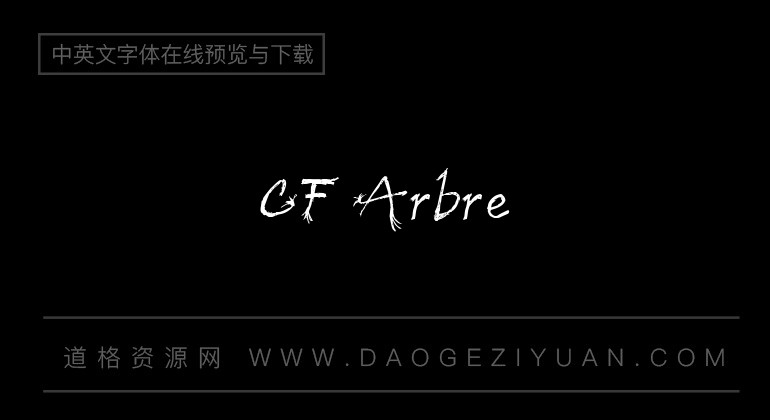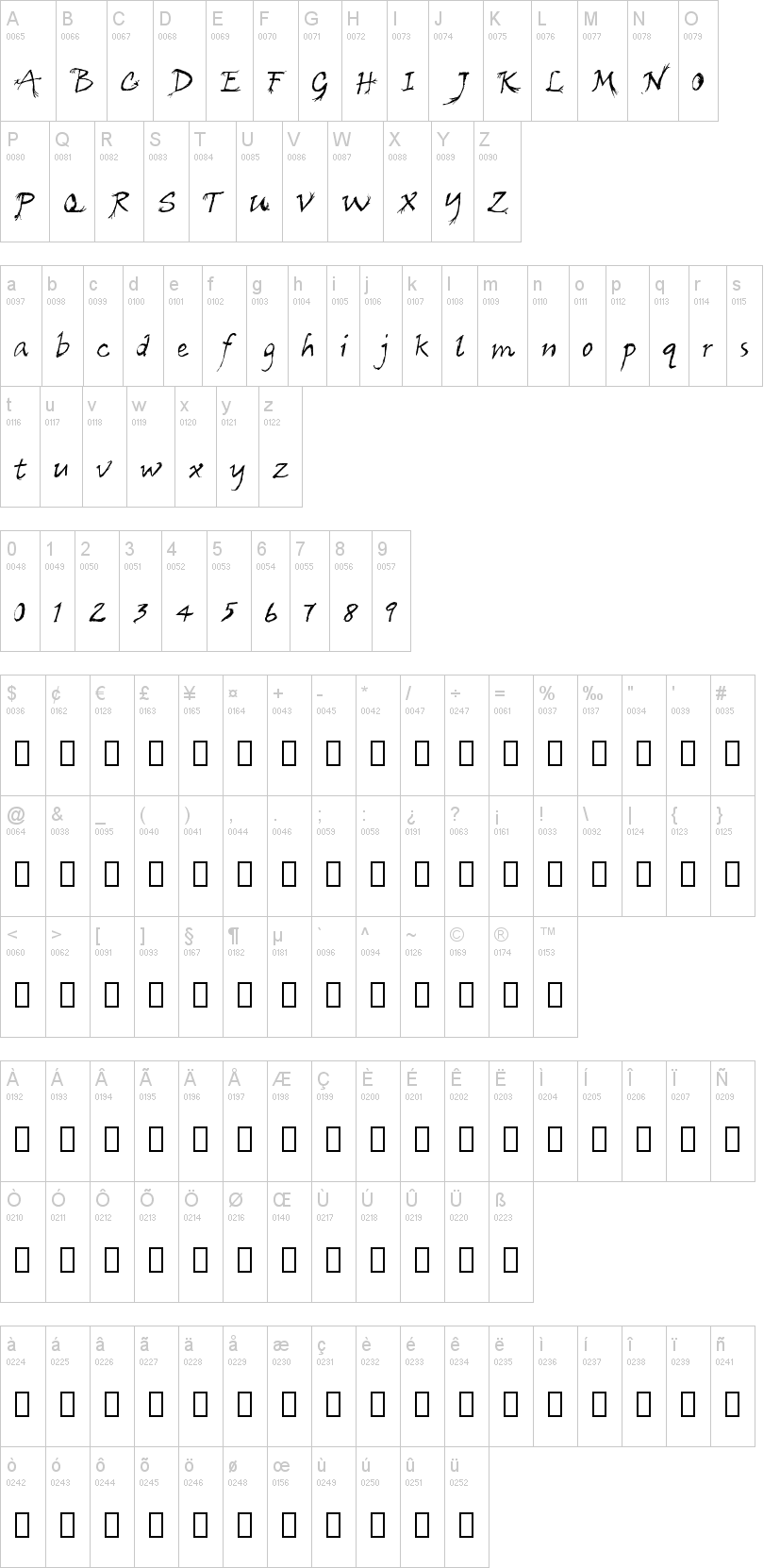
? CF Arbre 是一款由 Creative Fabrica 开发的显示字体,它具有简洁而又精致的外观,是一款优雅的字体,可以用于标题、标签和抬头。它的字体结构显示出精致的细节,而且它的字体风格也比较柔和,适合用于各种不同的设计项目。CF Arbre 字体具有极高的可读性,可以使您的设计更加精美,而且它还可以用于多种语言,这使您可以更轻松地将设计应用到全球范围内。内容介绍
CF Arbre是一款非常不错的手写艺术字体,具有很好的视觉感,适合于文化类的宣传设计、商业类品牌的广告和产品包装设计以及个性化文字排版等较多场景。